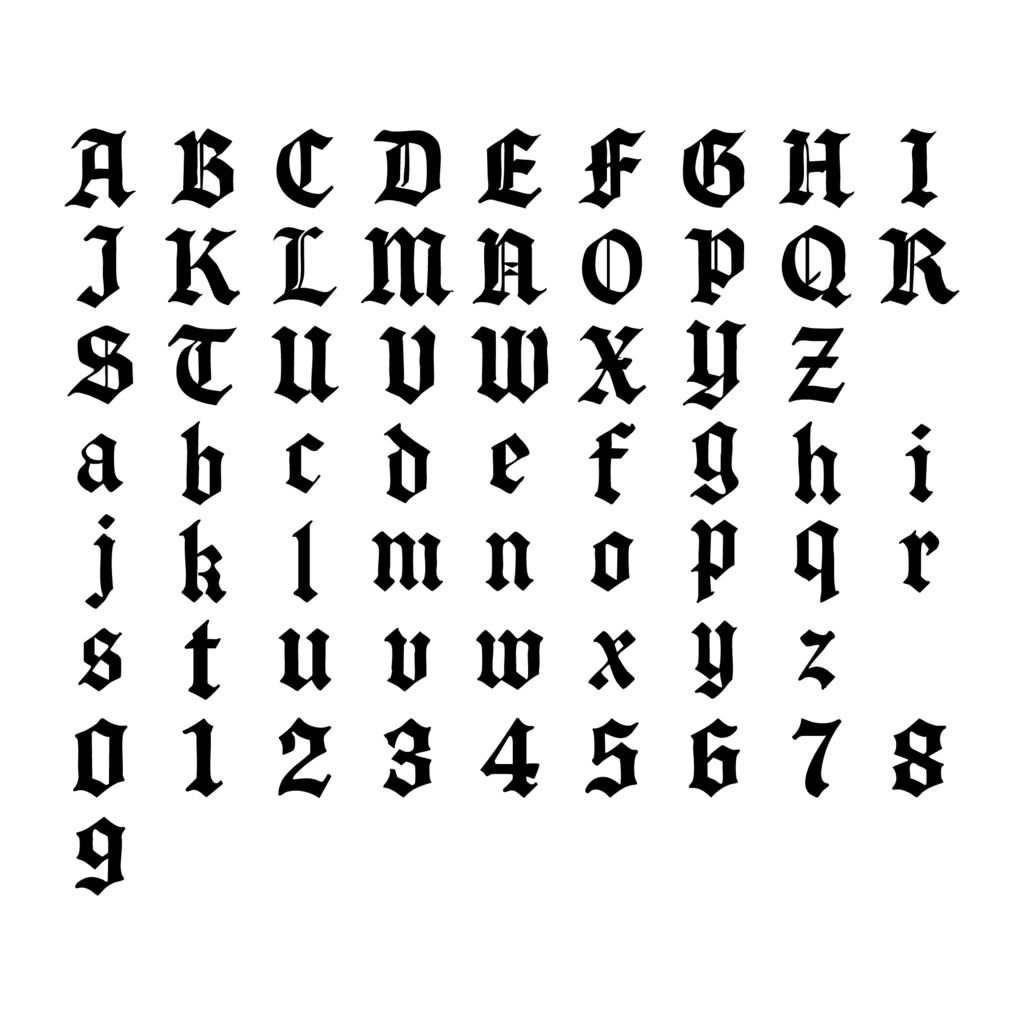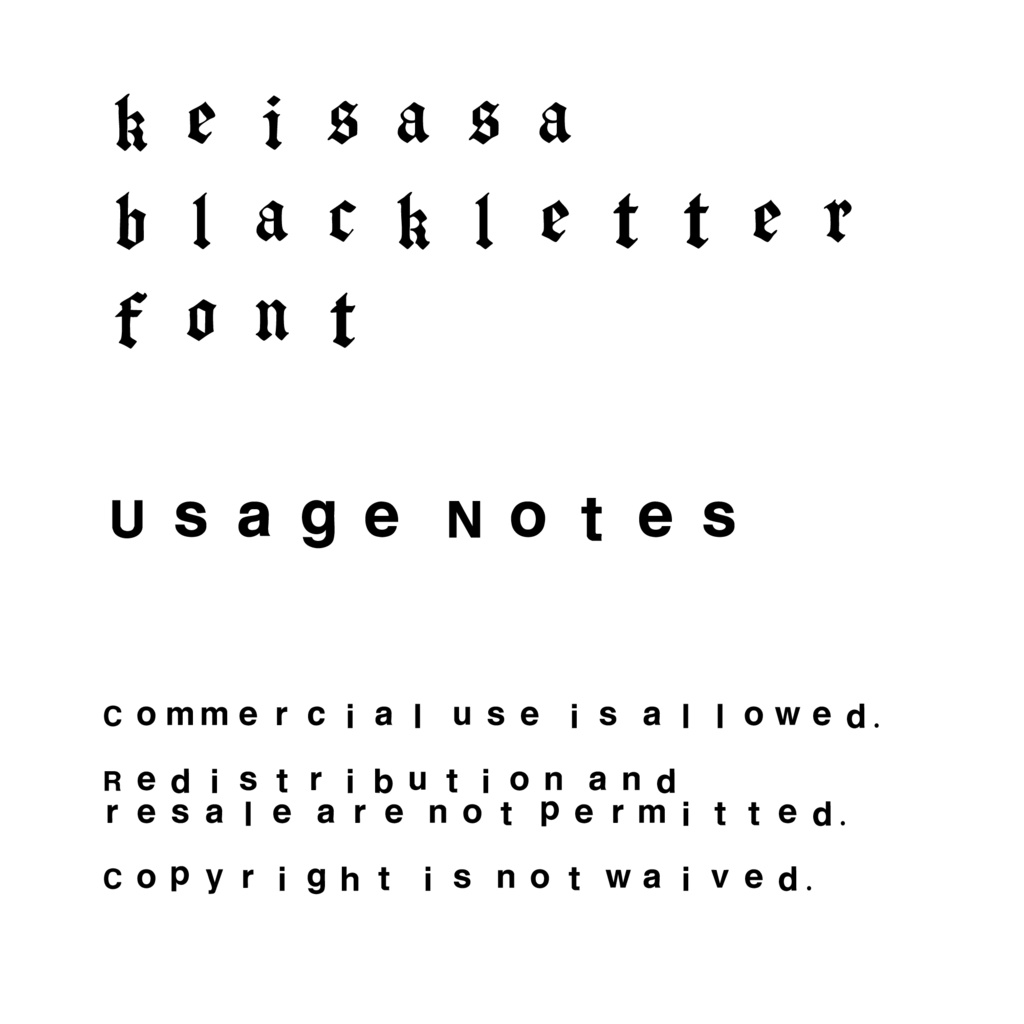
【商用可】keisasa blackletter font|中世系手描きゴシックフォント
keisasa blackletter font は、中世ヨーロッパの写本を思わせる重厚な手描きブラックレター書体です。 鋭いラインと装飾的なフォルムが、デザインに圧倒的な存在感を与えます。 ロゴ、ポスター、パッケージ、タイトルデザインなど、強い印象を残したいシーンに最適です。 商用利用可 再配布・再販売不可 著作権は放棄しておりません keisasa blackletter font brings the bold elegance of medieval European manuscripts to your designs. Its sharp lines and ornate letterforms deliver a striking visual impact, perfect for logos, posters, packaging, and title work. Commercial use allowed Redistribution and resale prohibited Copyright not waived